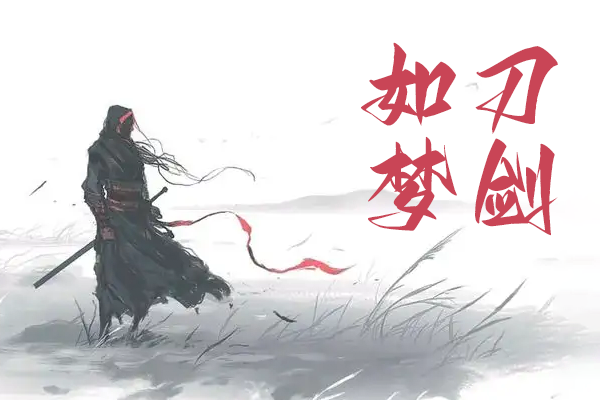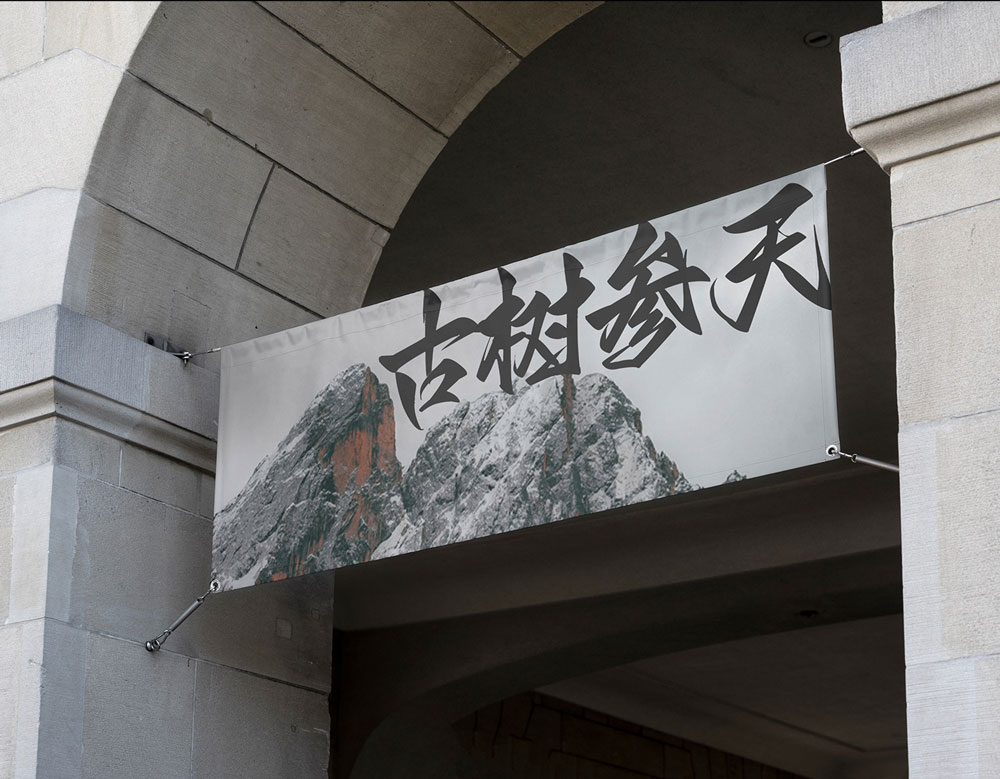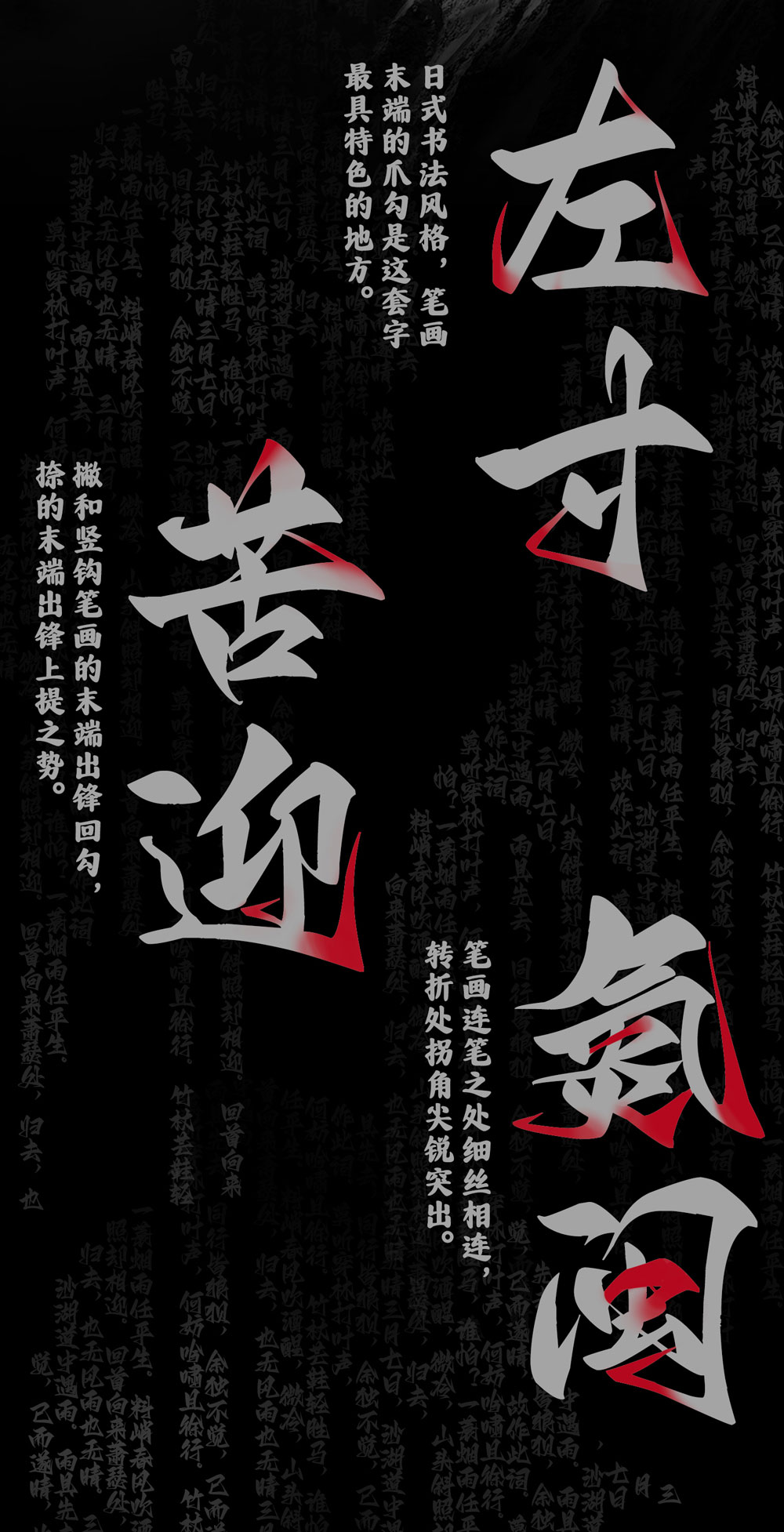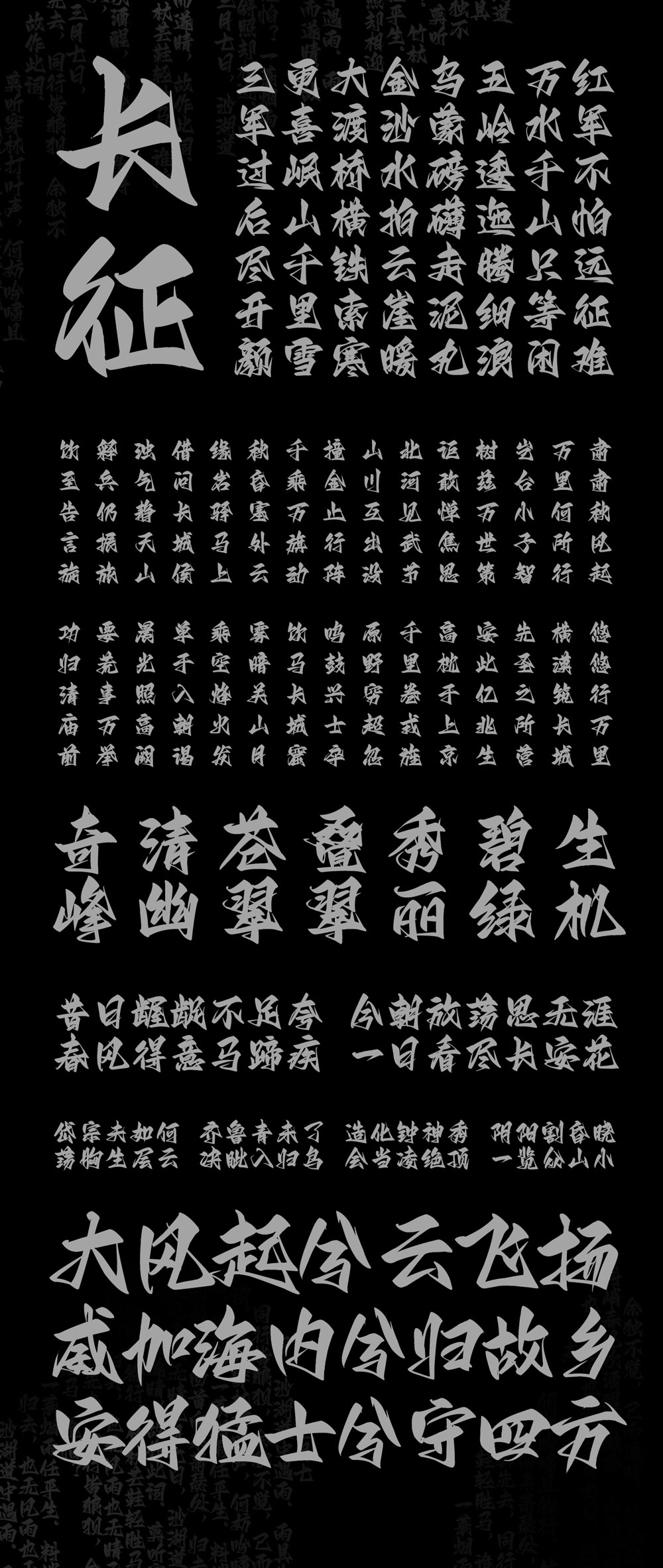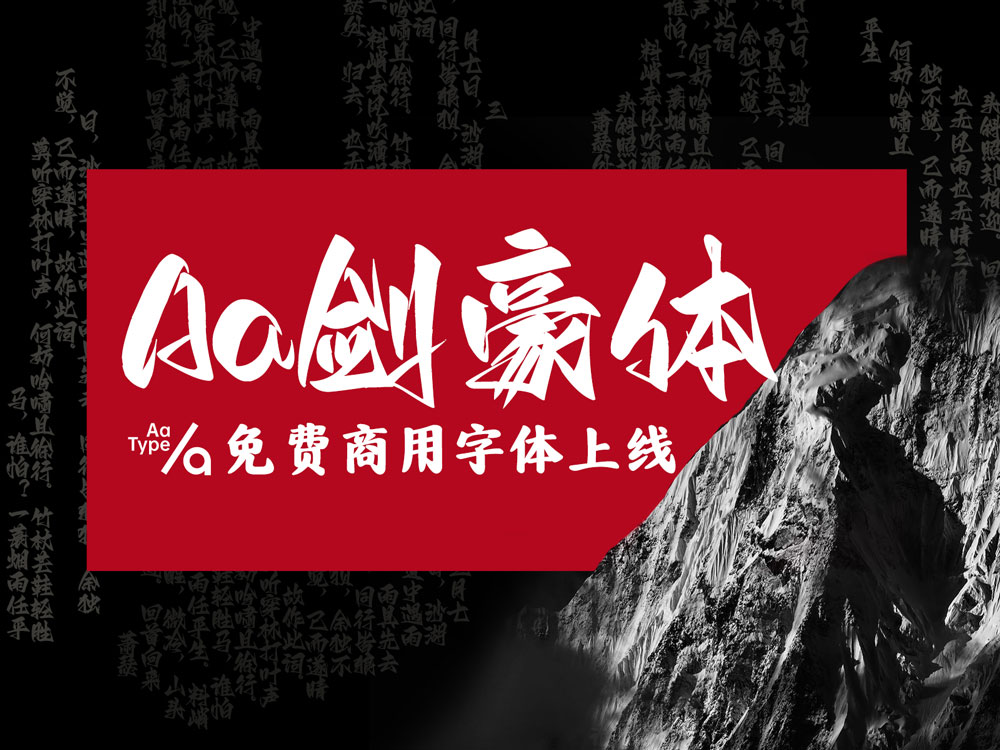
Aa剑豪体
Aa剑豪体是Aa字库推出的一款免费商用字体,手写风格,字体名如其实,张狂有劲,仿佛剑豪的招式,非常好看。官方声明该字体为免费商用。
该字体是Aa字库的首款免费商用字体,透着一股江湖豪气,洒脱豪放,适合应用于各种艺术字体,如平面设计、网页设计,书法字帖等领域。
Aa剑豪体效果预览
Aa剑豪体字体效果预览